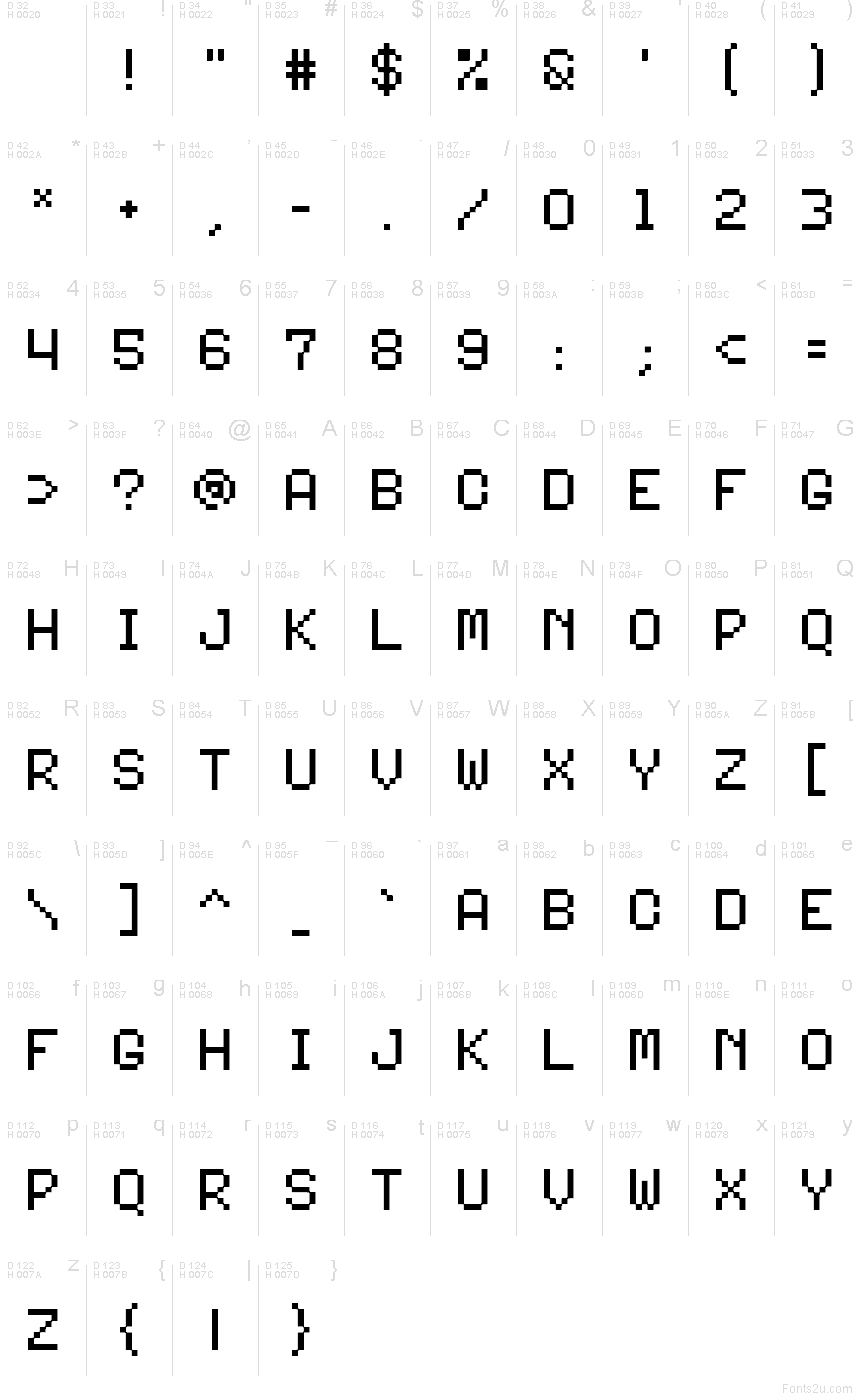
Pixfay é uma fonte bitmap pixelada gratuita da Ermedia Studio, criada com maiúsculas robustas da era dos games e traços quadrados rígidos. Suas letras utilizam blocos largos, cantos cortados e espaçamentos compactos para criar um ritmo de baixa resolução deliberado.
Esta fonte gratuita é ideal para títulos de jogos retrô, pôsteres de arcade, embalagens pixel-art, gráficos de streaming e banners de eventos de tecnologia. Use-a em manchetes curtas, capas, cartões de título ou monogramas, onde seu lettering em blocos transmite uma forte estética 8-bit.